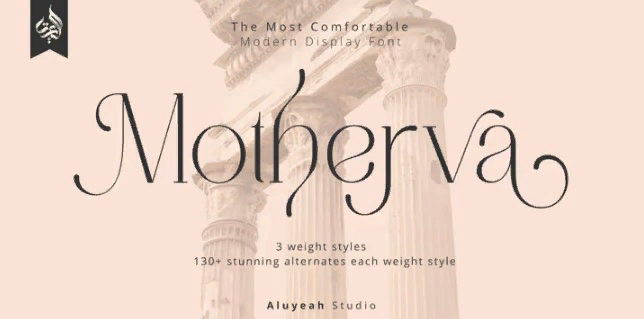
Motherva, самый удобный современный дисплейный шрифт.
Поставляется с 3 весовыми стилями. 130+ потрясающих и очень простых в использовании альтернатив для каждого стиля.
Очень подходит для журнала, заголовка, веб-сайта, рекламы, упаковки продукта и всех типов дизайнерских проектов, которые у вас есть.